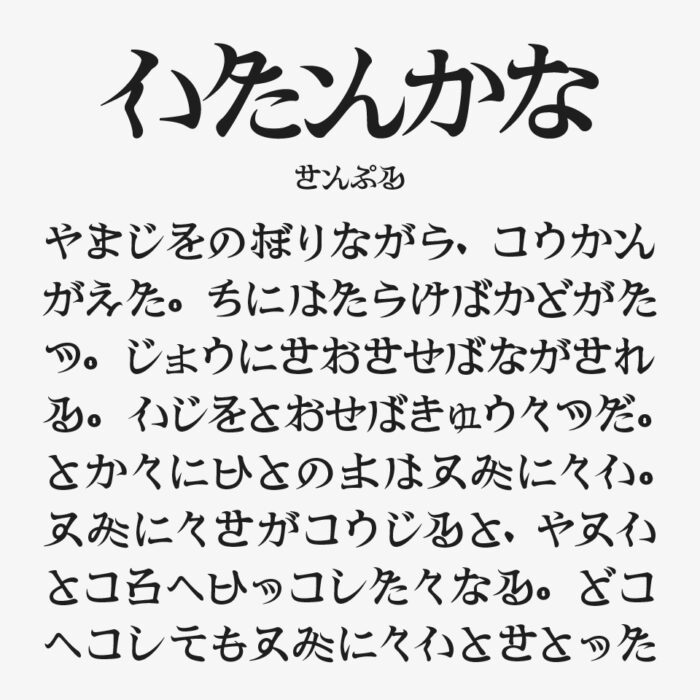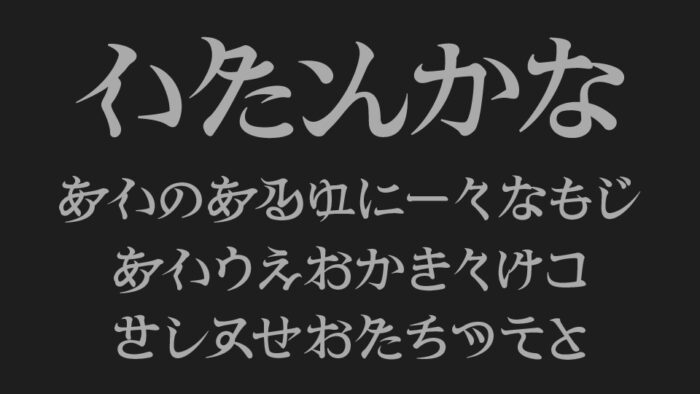
異端仮名『怪』フォントは、ひらがなとカタカナの融合した異形の文字にゾクゾクとしてしまうユニークなデザインフォントです。
ひらがなとカタカナが組み合わさって作れらていることで「これはなんだろう?」と一見ギョッとしてしまう形ながら、よく見ると読めてしまう不思議なフォントです。古典的な雰囲気を持ちながらも、現代的にアレンジされているデザインがとても素敵です。
収録文字は、ひらがな・一部記号が収録されています。